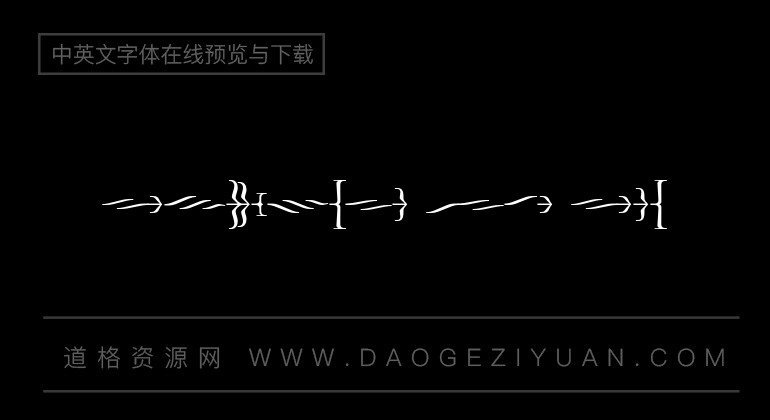
Foglihten Deco Font
Foglihten Deco是一种装饰性的字体,其设计灵感来自于20世纪20年代的艺术风格,尤其是装饰艺术运动。它的特点是线条流畅、几何化的形状和装饰性的元素,使其适合用于标题、海报、广告和其他需要吸引眼球的设计项目。 Foglihten Deco字体由设计师Gluk设计,提供了多种不同的字形和大小,方便设计师进行排版和排版方案的调整。它的设计灵感来自于艺术家们在20世纪20年代所设计的艺术品和印刷品,使其成为一种有着深厚历史背景的字体。 Foglihten Deco字体的特点是它的线条流畅、几何化的形状和装饰性的元素,使其适合用于有需要突出视觉效果的设计项目。如果您正在寻找一种具有装饰性的字体,可以尝试使用Foglihten Deco字体进行设计。
Foglihten Deco Font是一款非常不错的手写艺术字体,具有很好的视觉感,适合于文化类的宣传设计、商业类品牌的广告和产品包装设计以及个性化文字排版等较多场景。